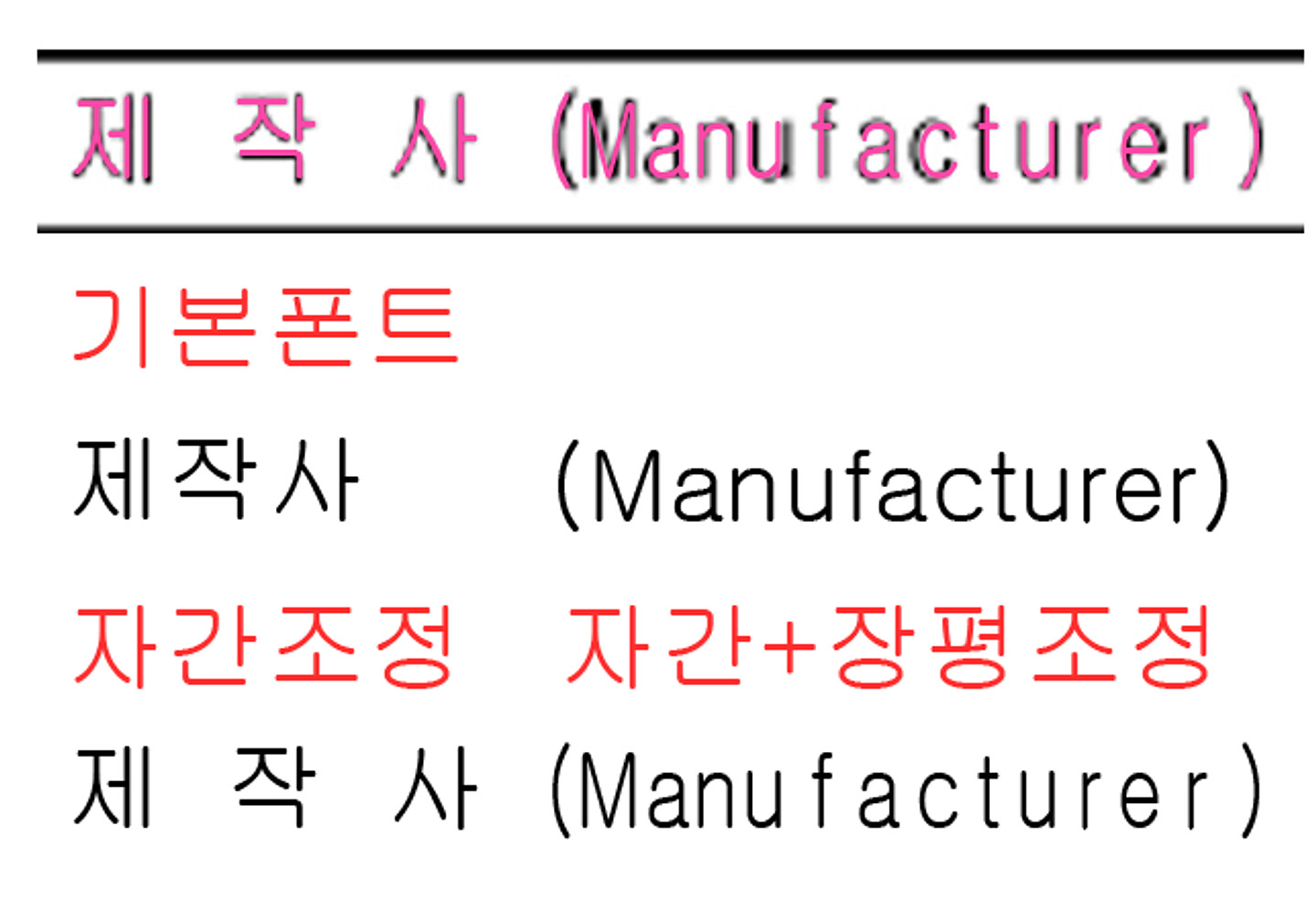
영어랑 한글이랑 섞여 있는데, 이게 하나의 폰트인건지 모르곘네요. 고딕체 같은데 고딕체로 하면 살짝 다릅니다. 영어의 경우에는 글자 폭은 좁고 글자 끼리의 간격은 약간 넓구요.
굴림
윈도우 기본폰트 굴림입니다! 한글은 기본폰트에서 자간을 엄청 늘렸고, 영어는 자간이랑 장평 둘 다 조정되었네요!